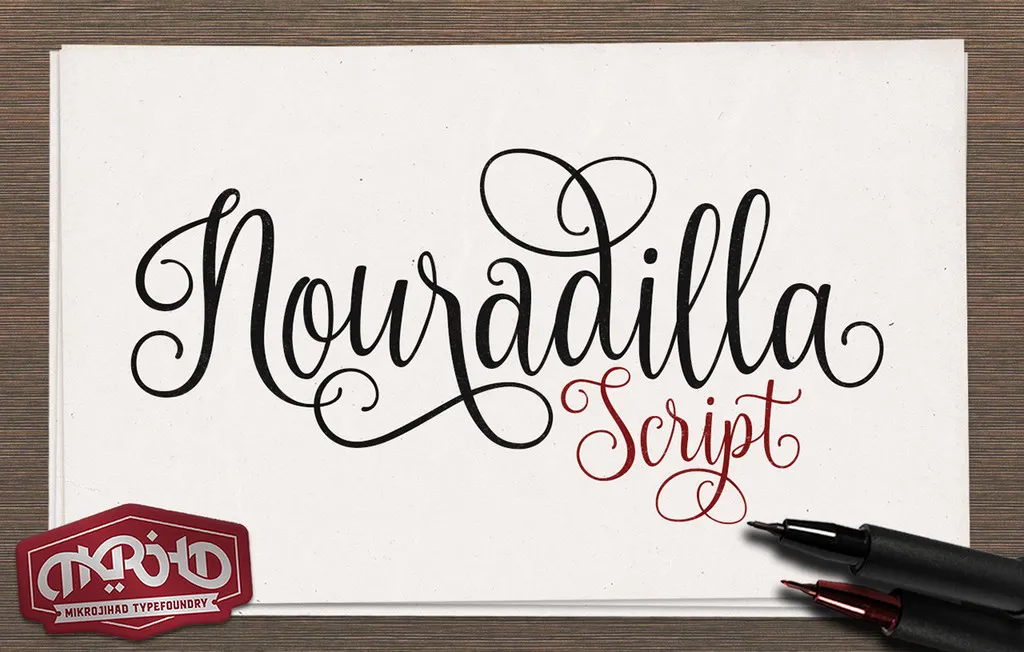
A Nouradilla é uma tipografia moderna e experimental que mistura elementos do caligrafismo. Com base linhas superiores e inferiores, essa fonte oferece uma rica gama de 413 caracteres. Além disso, a Nouradilla suporta alternâncias estilizadas, ligantes e alternativas contextualas, permitindo até 16 variantes por letra. A Hamilton é o designer desta fonte experimental, que se destaca não apenas pela sua aparência única, mas também pela facilidade de customização e personalização de suas letras. Se você busca uma maneira moderna de incorporar um toque de originalidade em seus projetos, a Nouradilla é uma ótima escolha para explorar.